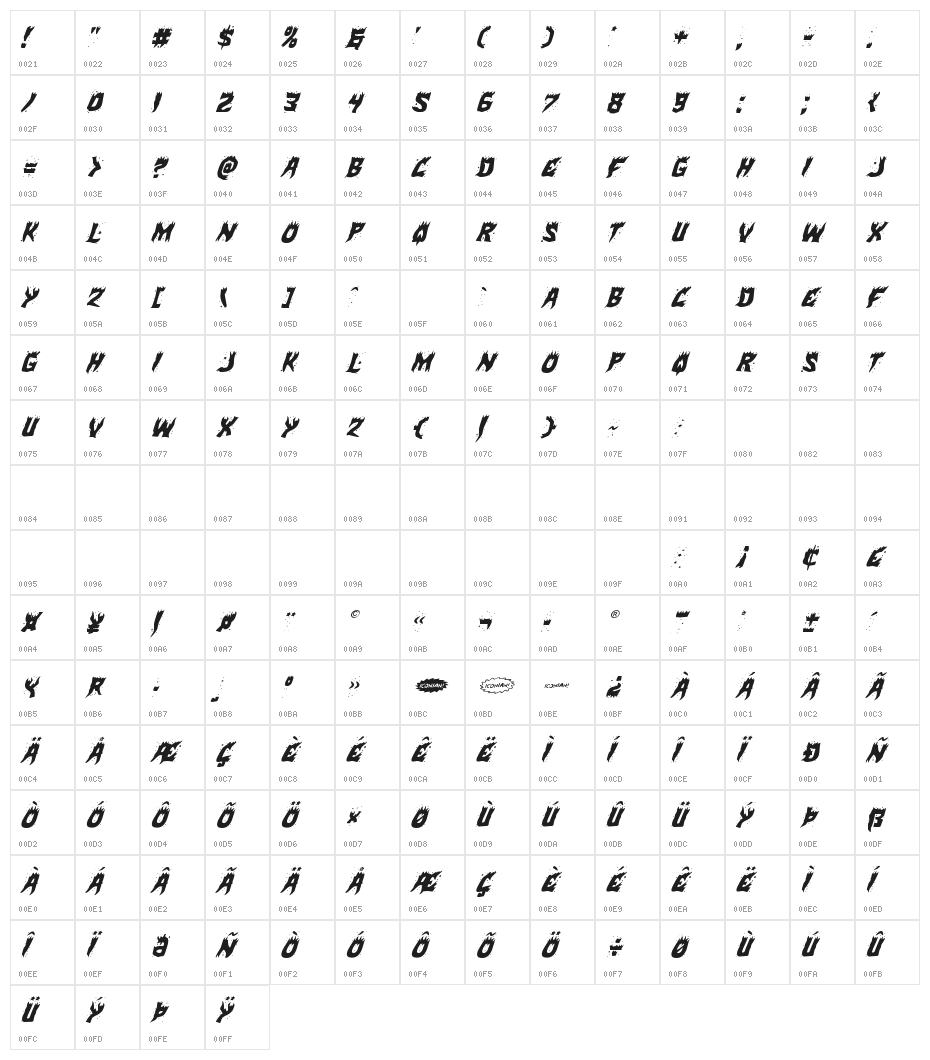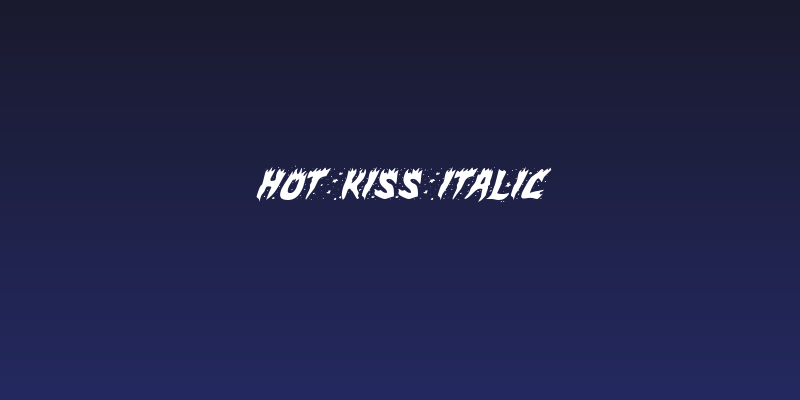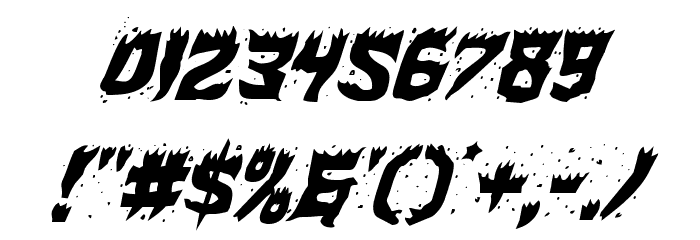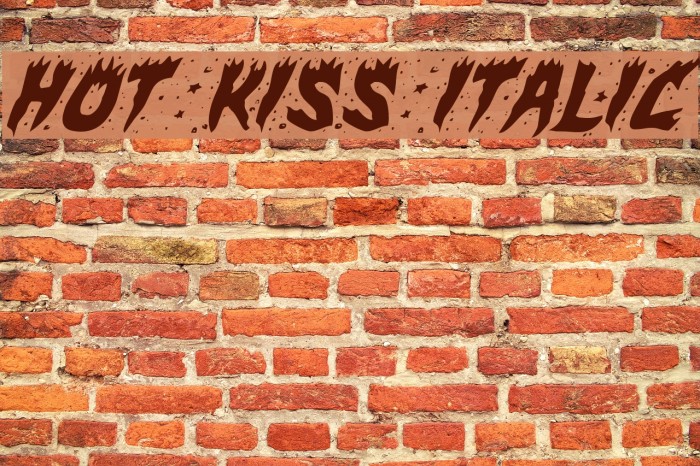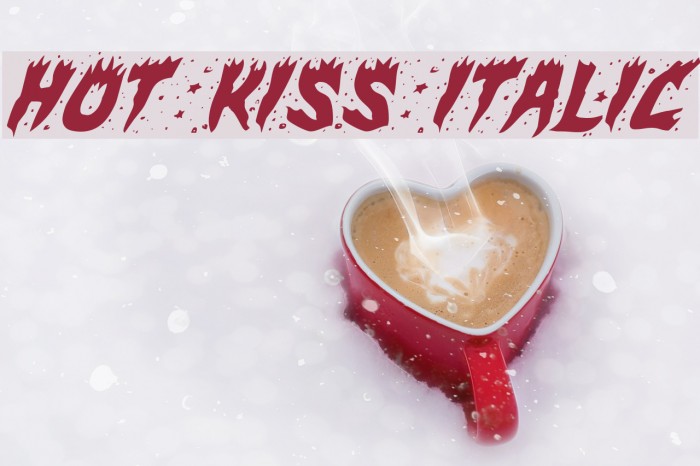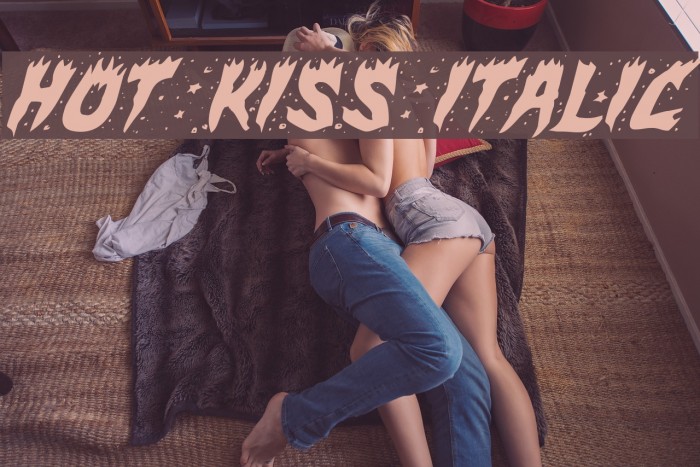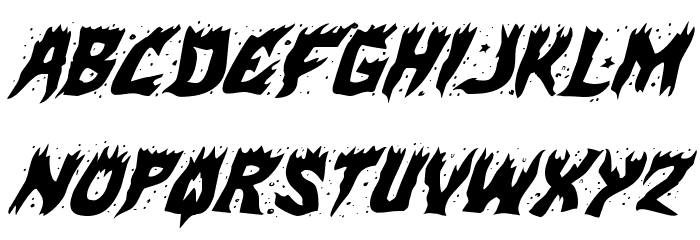
Hot Kiss Italic Font
| Estilo general | Modern, Edgy |
| Proyectos propuestos | Ideal for music album covers, event posters, video game titles, and any project requiring a bold, eye-catching typeface. |